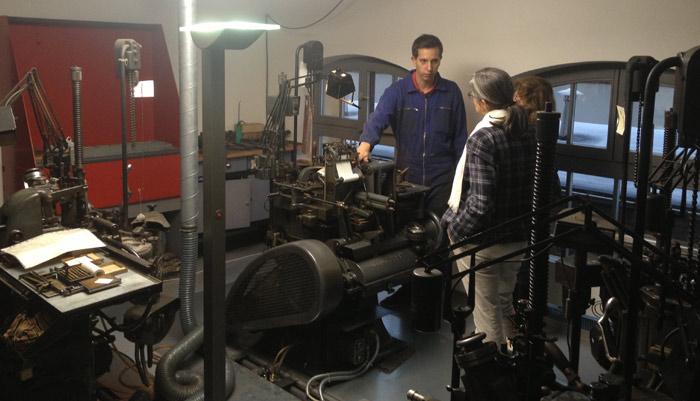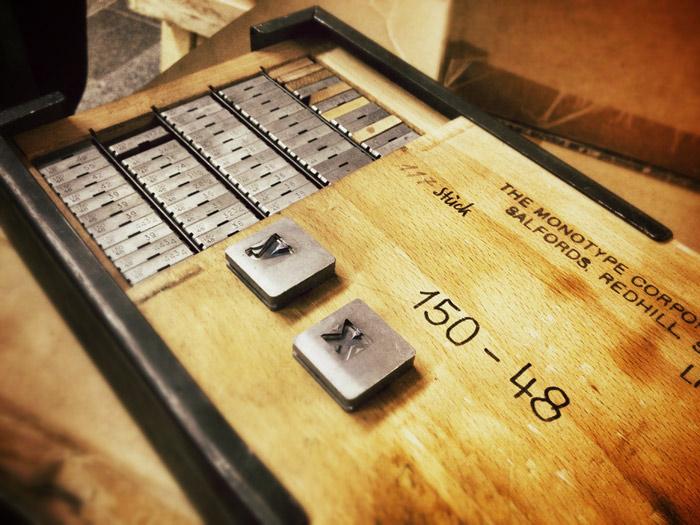
Hand- und Maschinensatz gelten als antiquiert, die Maschinen und Lettern benötigen viel Platz und die Herstellung einer Druckseite ist zeitaufwendig, mühsam, unwirtschaftlich. Und dennoch ist da eben auch der Klang der Gieß- und Druckmaschinen, der Geruch der Werkstatt, das Vergnügen, etwas mit den Händen zu erschaffen. Und schließlich die luxuriöse Haptik, die unvergleichliche Schönheit und die handwerkliche Qualität des Buchdrucks.
In der Offizin Haag-Drugulin in Dresden existiert ein großer Reichtum an Blei- und Holzlettern, Matrizen und imposante Druck- und Satzgießmaschinen. Hunderte wunderschöner Originalschriften von berühmten Stempelschneidern warten teilweise noch unausgepackt in der Lagerhalle darauf, von gekonnten Händen gesetzt und gedruckt zu werden.
Eine neue Generation verliebt sich gerade in den Bleisatz. Für sie ist dies eine erfrischende Form des Ausdrucks, die so viel mehr Dimensionen besitzt als flache und leblose Offset- und Digitaldruckstücke. Mit einem Förderverein soll jungen Menschen aus aller Welt die Möglichkeit gegeben werden, in der Dresdner Handsatzwerkstatt selber mit allen Sinnen zu entwerfen, zu gestalten, zu setzen und das eigene Werk schließlich selbst zu drucken. Außerdem soll mit Dozenten ein zugehöriges Fortbildungsprogramm für Handsatz auf die Beine gestellt werden.